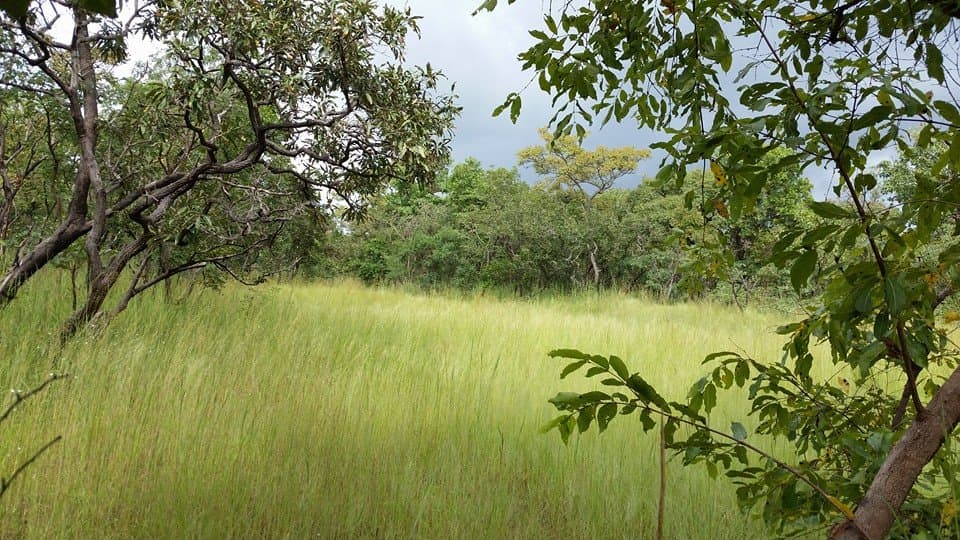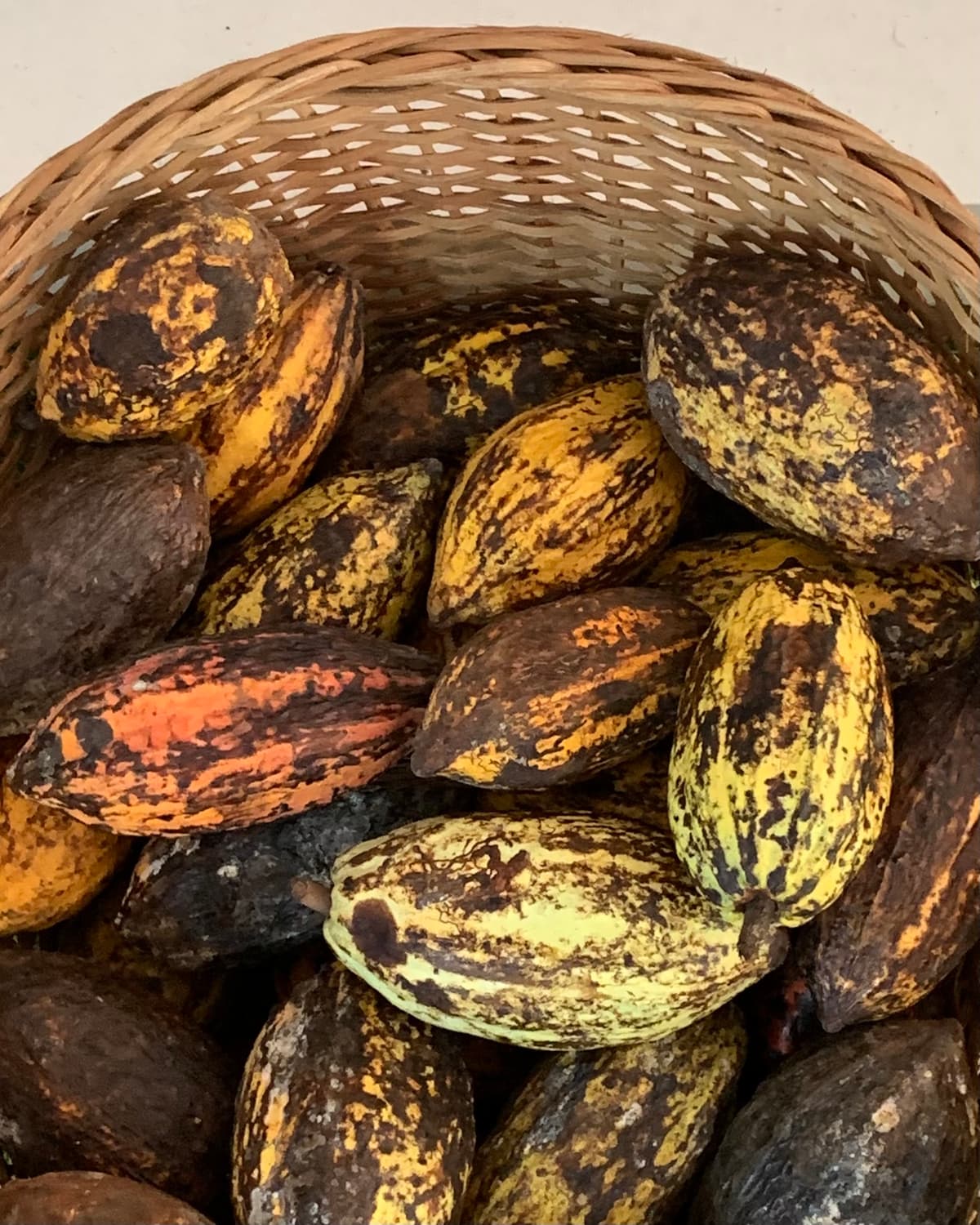
OS Nadrey Cacao
Chocolettres dorées.
Cœur de cacao.
ALT Nadrey était une police publiée avec une fonderie anglaise parce que je pensais avoir besoin de la validation occidentale pour réussir dans le dessin de caractères, jusqu'à ce que je constate qu'en indépendant je faisais plus de ventes qu'avec eux. Je les ai quittés pour construire le monde où la Côte d’Ivoire décide de la valeur de ses productions, et dicte les termes d’échange. Nadrey édition Cacao est offerte aux individus et collectifs basés en Côte d’Ivoire. Pour tout le reste: Cette police n'est pas à vendre. - O'Plérou 🫗